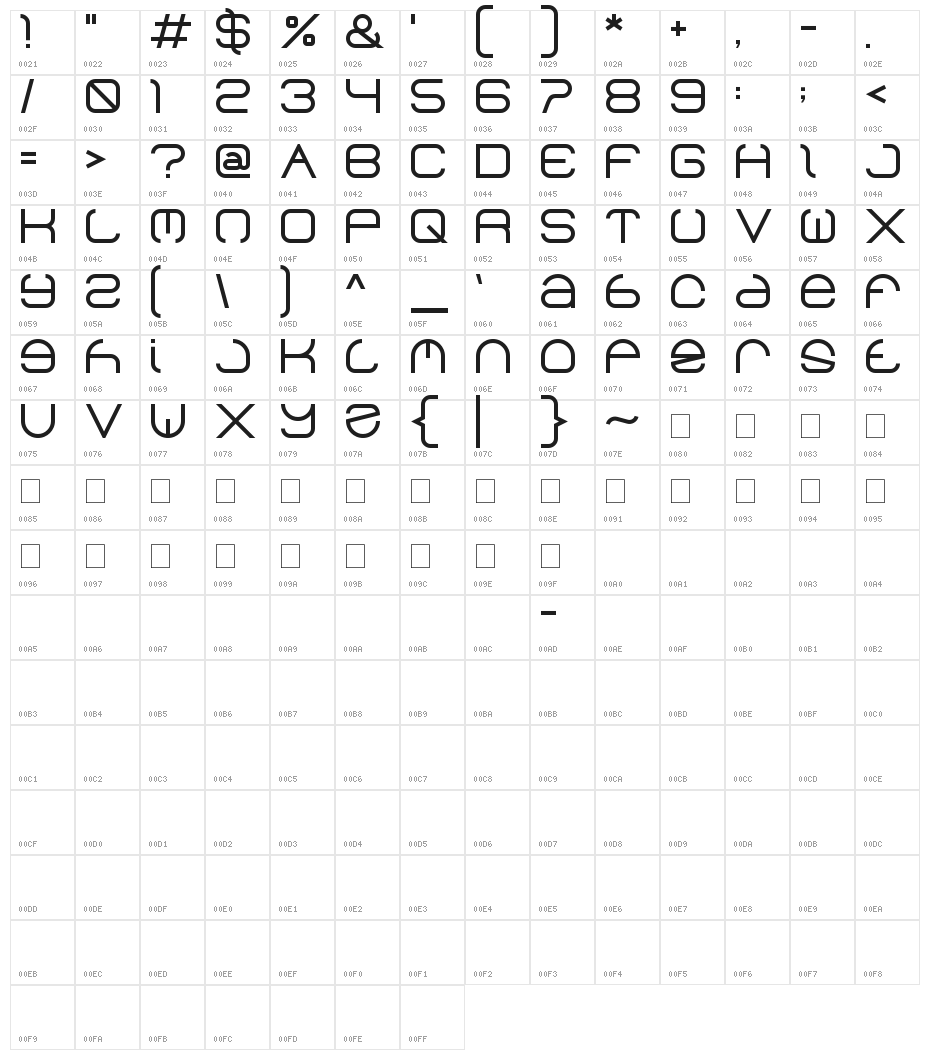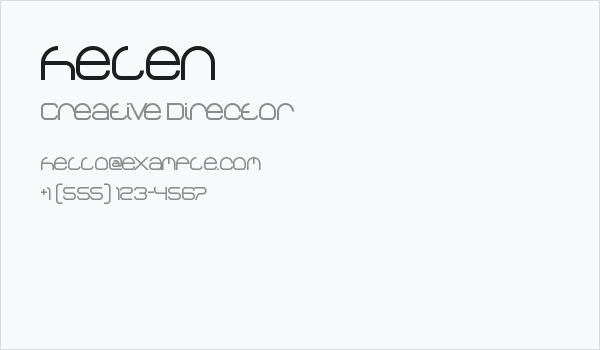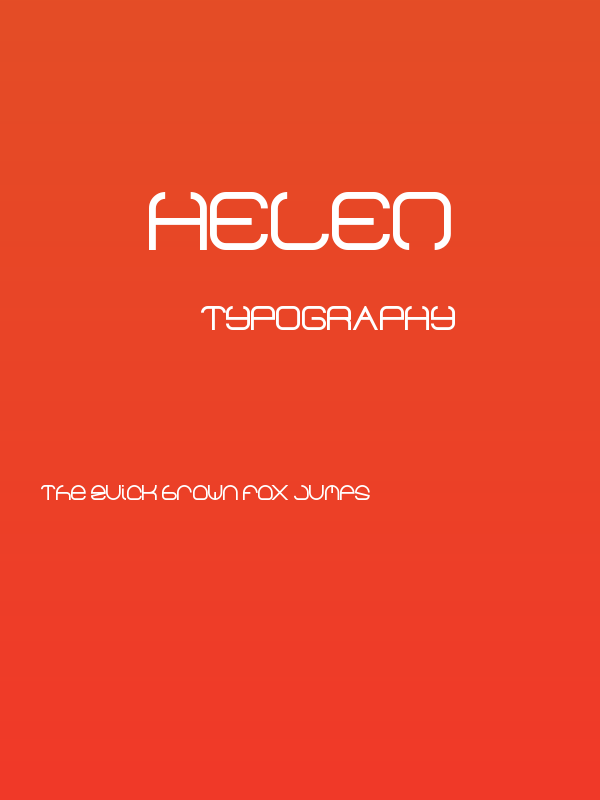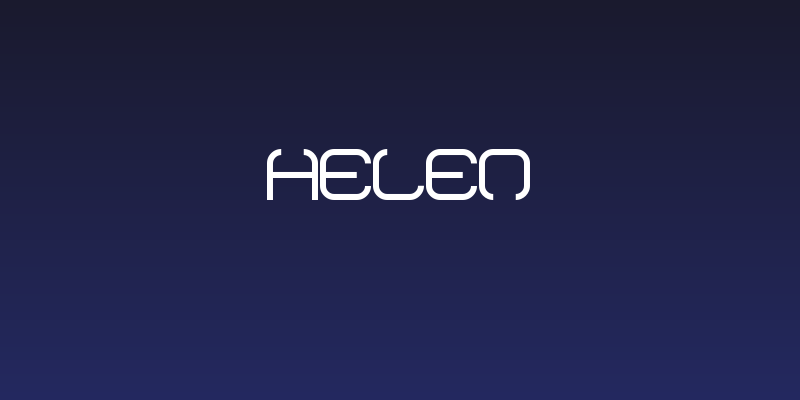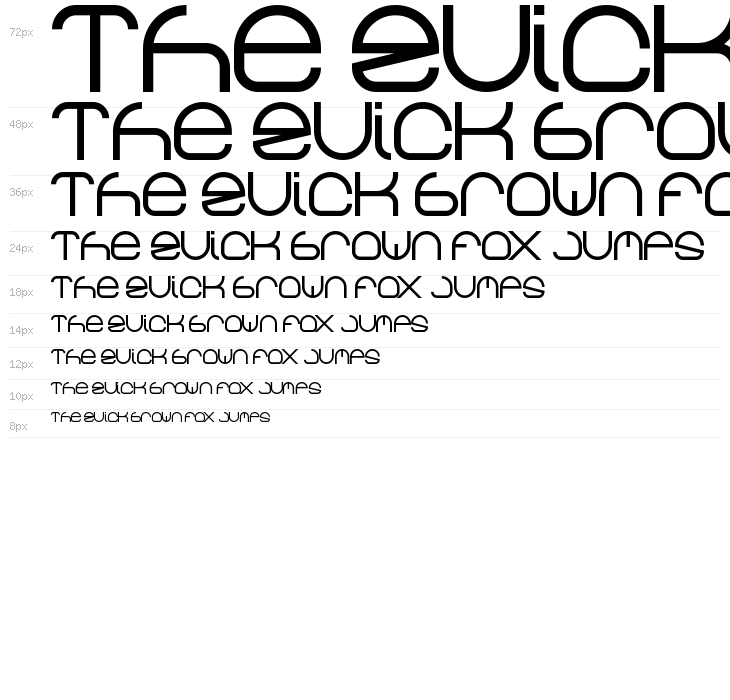
helen Font
| Stile generale | Futuristic |
| Caso d'uso | Logos, Headlines, Branding |
| Progetti proposti | Ideal for technology branding, sci-fi themed projects, modern advertising, and innovative product packaging. |